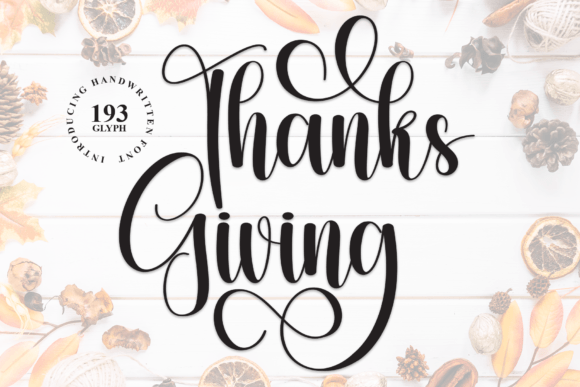
Thanks Giving
Thanks Givingのような高品質の素材をお探しの場合、このプレミアムパッケージはクリエイティブなプロジェクトに素晴らしい選択です。
POD(オンデマンド印刷)製品、結婚式の招待状、またはソーシャルメディアのグラフィックを作成している場合でも、Thanks Givingは理想的です。